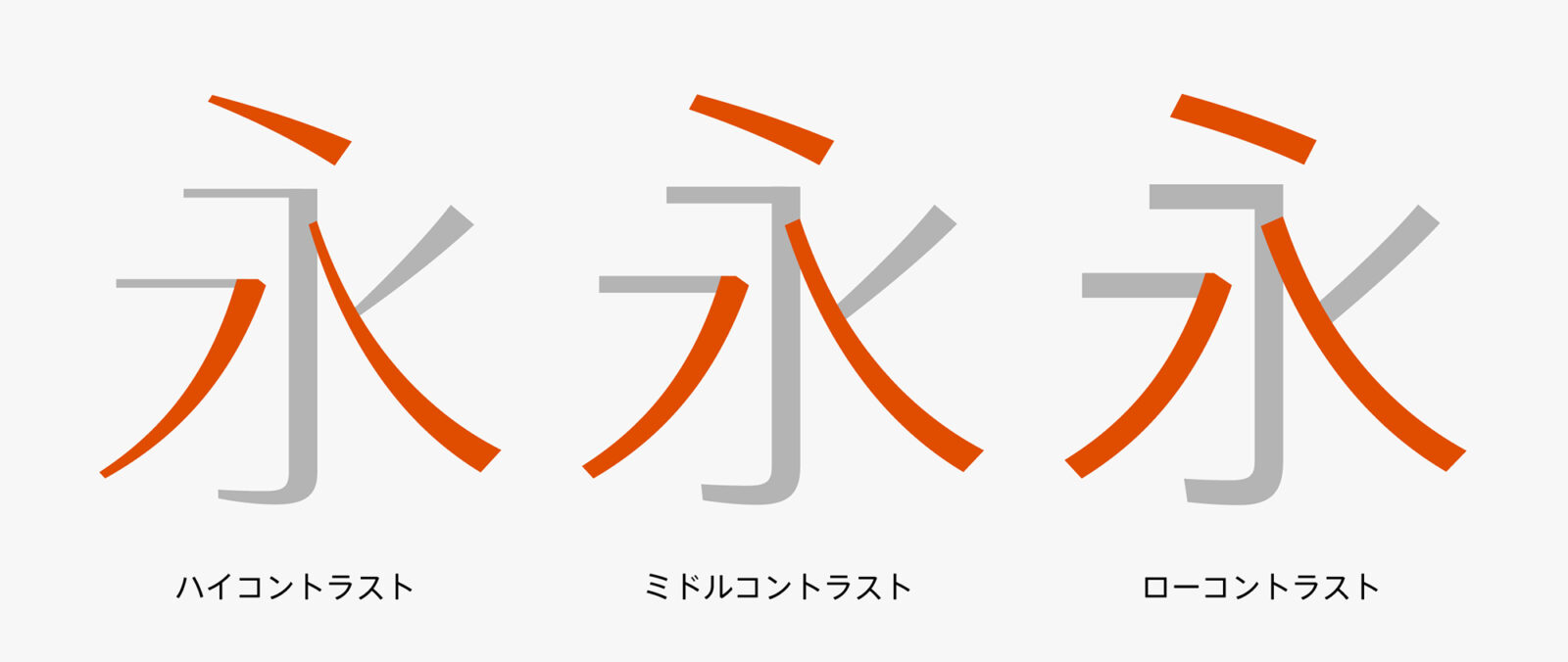
タイププロジェクト、TPスカイ クラシックシリーズの拡張を発表
筆の抑揚を取り入れた古典的な表情の「ハイコントラスト」と「ミドルコントラスト」
タイププロジェクト株式会社(東京都練馬区 代表取締役社長 鈴木 功)は、スクリーン表示に最適な「TPスカイ」ファミリーに、シャープな印象のTPスカイ クラシック ハイコントラスト、穏やかながらも表情ゆたかなTPスカイ クラシック ミドルコントラストを追加したことを発表しました。本日より、タイププロジェクトのサブスクリプションサービス「TPコネクト」での提供を開始いたします。
TPスカイ クラシックの漢字・仮名・欧文を貫く均整の取れたプロポーションは、画面を引き締めると同時に落ち着いた雰囲気を醸し出します。引き締まったフトコロ(字画内の内部空間)と伸びやかなストロークの対比が持ち味で、フトコロ軸とコントラスト軸(ハイ、ミドル、ロー)の連携により、クラシックな印象を高めています。
「はらい」や「てん」などに筆の抑揚を取り入れたハイルコントラストとミドルコントラストでは、ローコントラストよりも古典的な表情が強まり、端正な古典楷書に範をとったTPスカイ クラシックの方向性をより明確に表しています。
タイププロジェクトの代表取締役 鈴木 功は、「ストロークの先端部に飾りがなく、抑揚の強弱がないサンセリフ体は、デジタル環境に適したシンプルさと安定した読み心地を持ち味とする一方、単調な表情になりがちです。TPスカイ クラシックでは、この主要な書体カテゴリーであるサンセリフ体に、フトコロの概念を導入することで現代的な用途の書体に古典的な表情を添えました。3つのコントラストが揃ったTPスカイ クラシックシリーズを楽しんでお使いいただけれと思います。」と述べています。
TPスカイファミリーは、TPスカイ45フォント(5ウエイト×3コントラスト×3つの字幅)、TPスカイ クラシック(5ウエイト×3コントラスト)、TPスカイ モダン ブラックで、合計61フォントのラインナップとなりました。